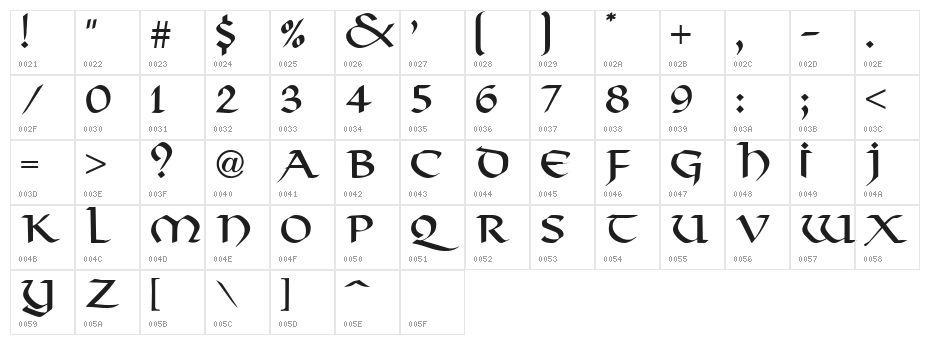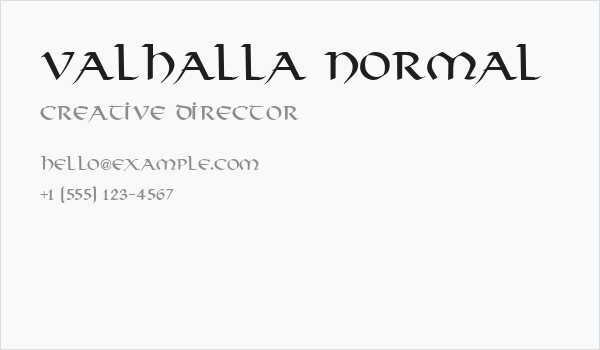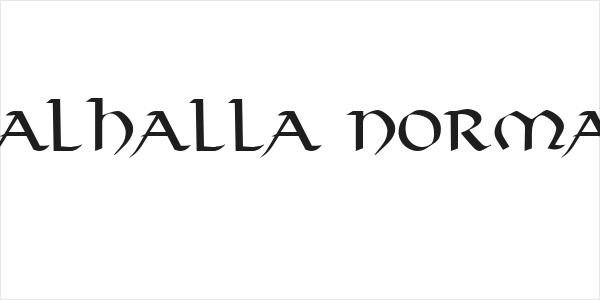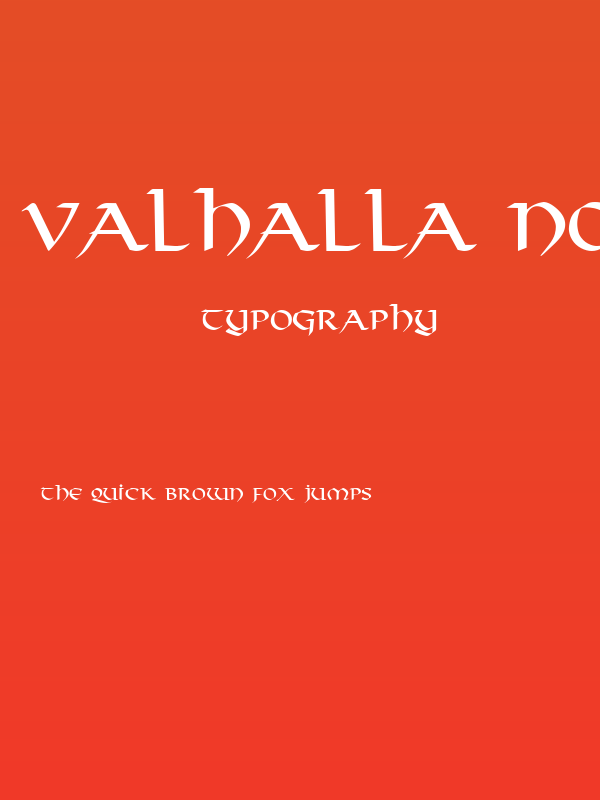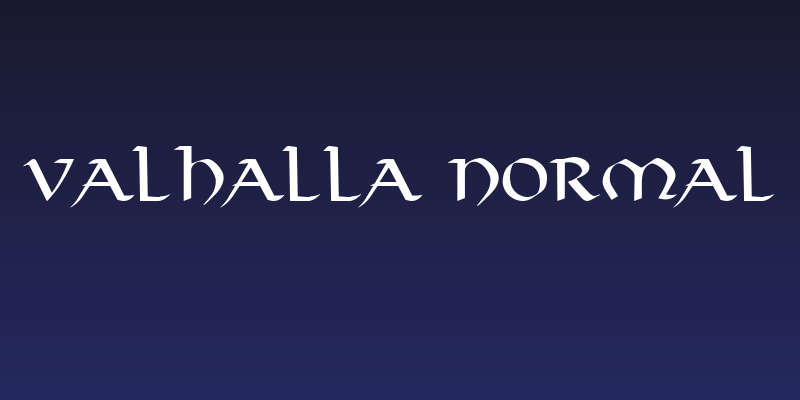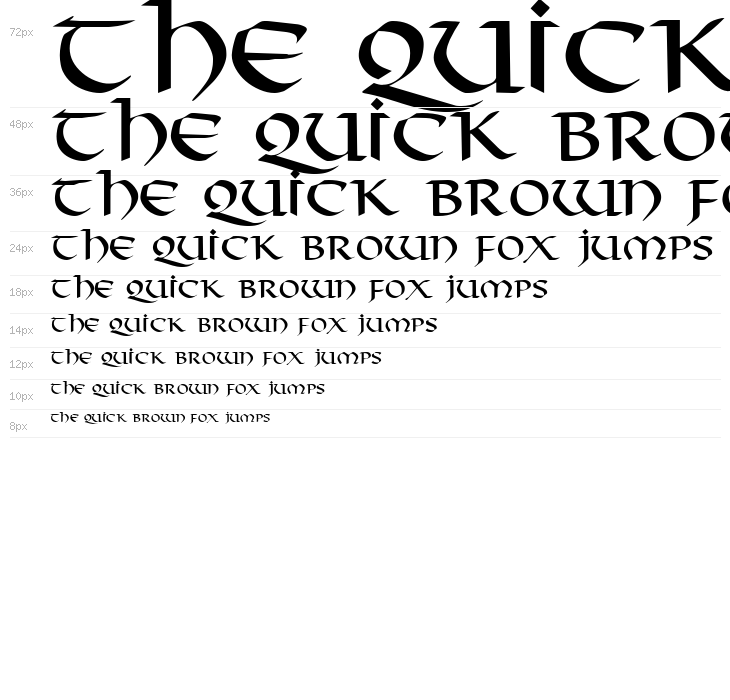
Valhalla Normal Font
| Name | Valhalla Normal |
| Gewicht | Normal |
| Kategorien | Gothic |
| Gesamtstil | Medieval, Decorative |
| Vorgeschlagene Projekte | Ideal for fantasy-themed projects, book covers, posters, and branding that requires a dramatic and historical touch. |